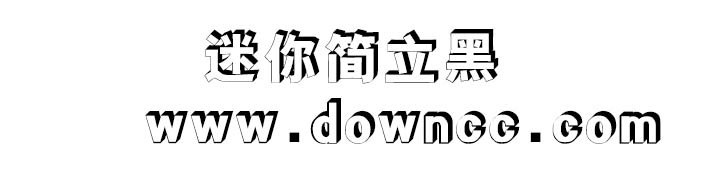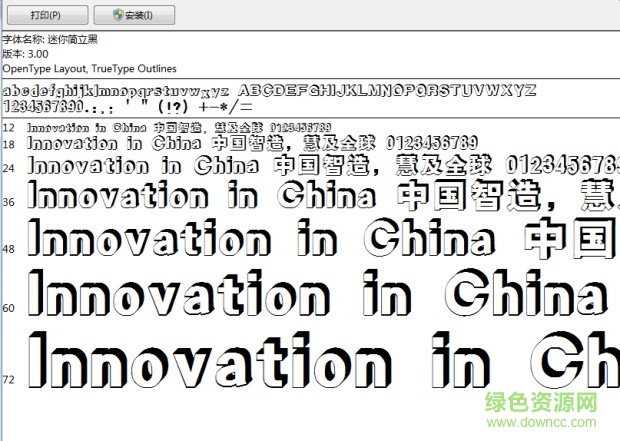
迷你簡(jiǎn)立黑字體一款迷你字庫(kù)中的字體,該字體具有很強(qiáng)的立體效果,字體端莊大方。非常適合用于名片設(shè)計(jì)、廣告設(shè)計(jì)、平面設(shè)計(jì)、雜志報(bào)刊等,有喜歡的朋友可以來(lái)綠色資源網(wǎng)下載使用!
迷你簡(jiǎn)立黑字體給人呈現(xiàn)的是一種立體的效果,字體的邊是黑色的,里面是空心的,適用在許多地方。